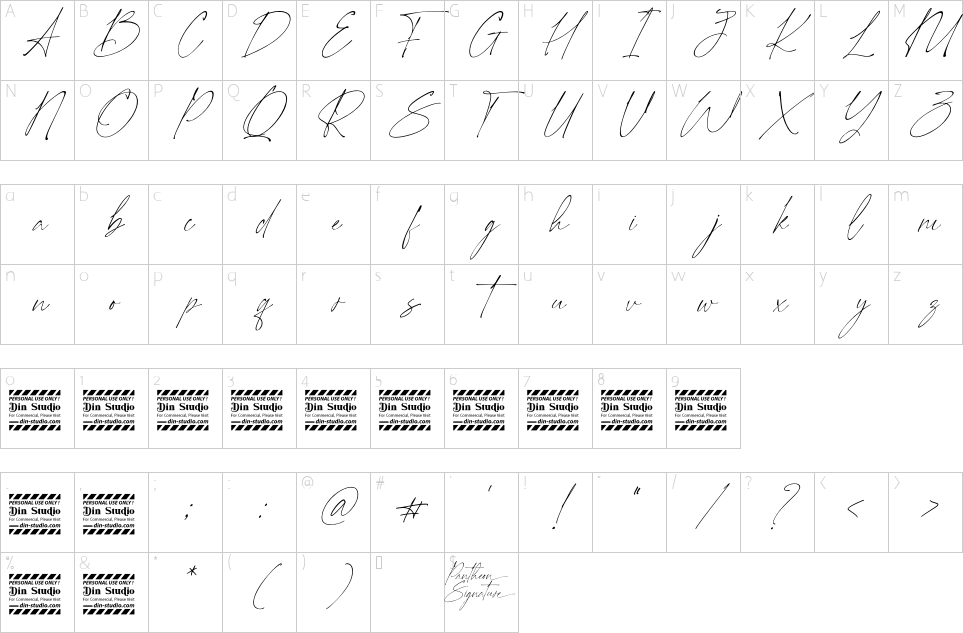
Pantheon é uma fonte elegante e moderna, perfeitamente adequada para qualquer projeto de design. Ela foi criada pela Din Studio e está disponível de forma gratuita para download tanto para Windows quanto para Mac. Suas linhas finas e bem equilibradas dão ao texto uma aparência sofisticada e moderna. Seja para textos de página principal, design de logotipo ou até mesmo para escrita em redes sociais, a Pantheon oferece uma escolha perfeita. Mais de 1.240 pessoas já aproveitaram seu download. Se você está buscando uma fonte gráfica perfeita para um projeto que exige elegância e qualidade, a Pantheon é uma escolha ótima.